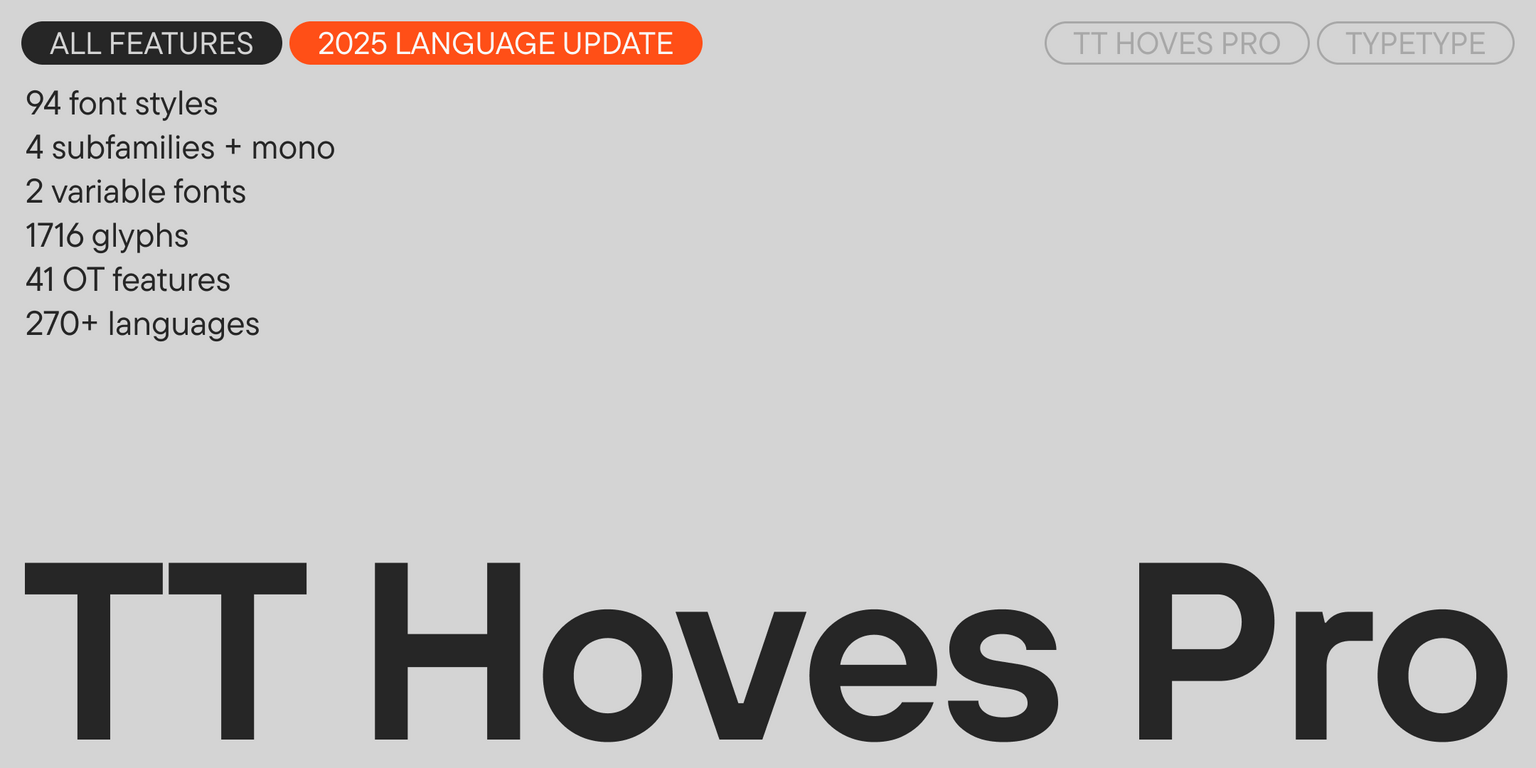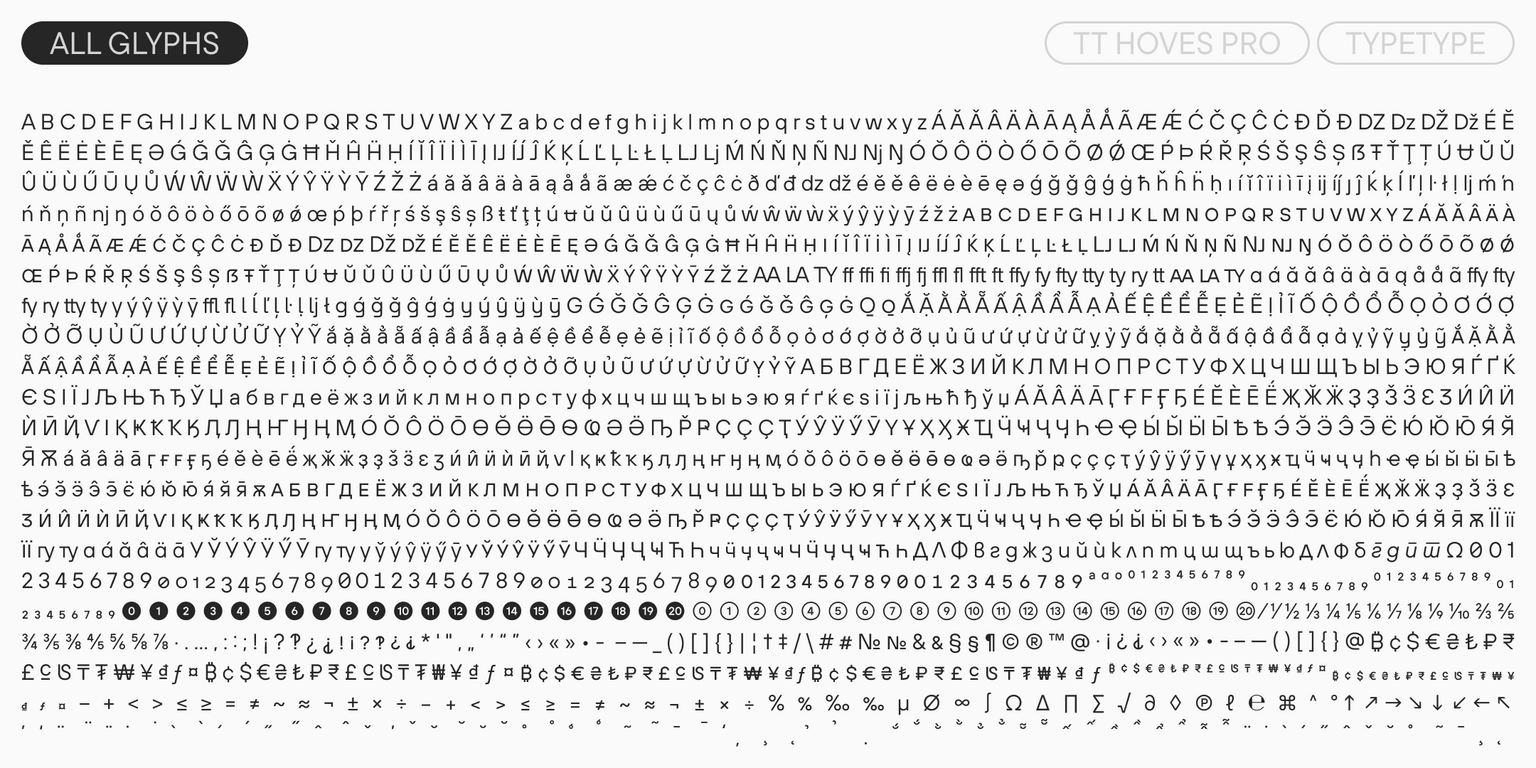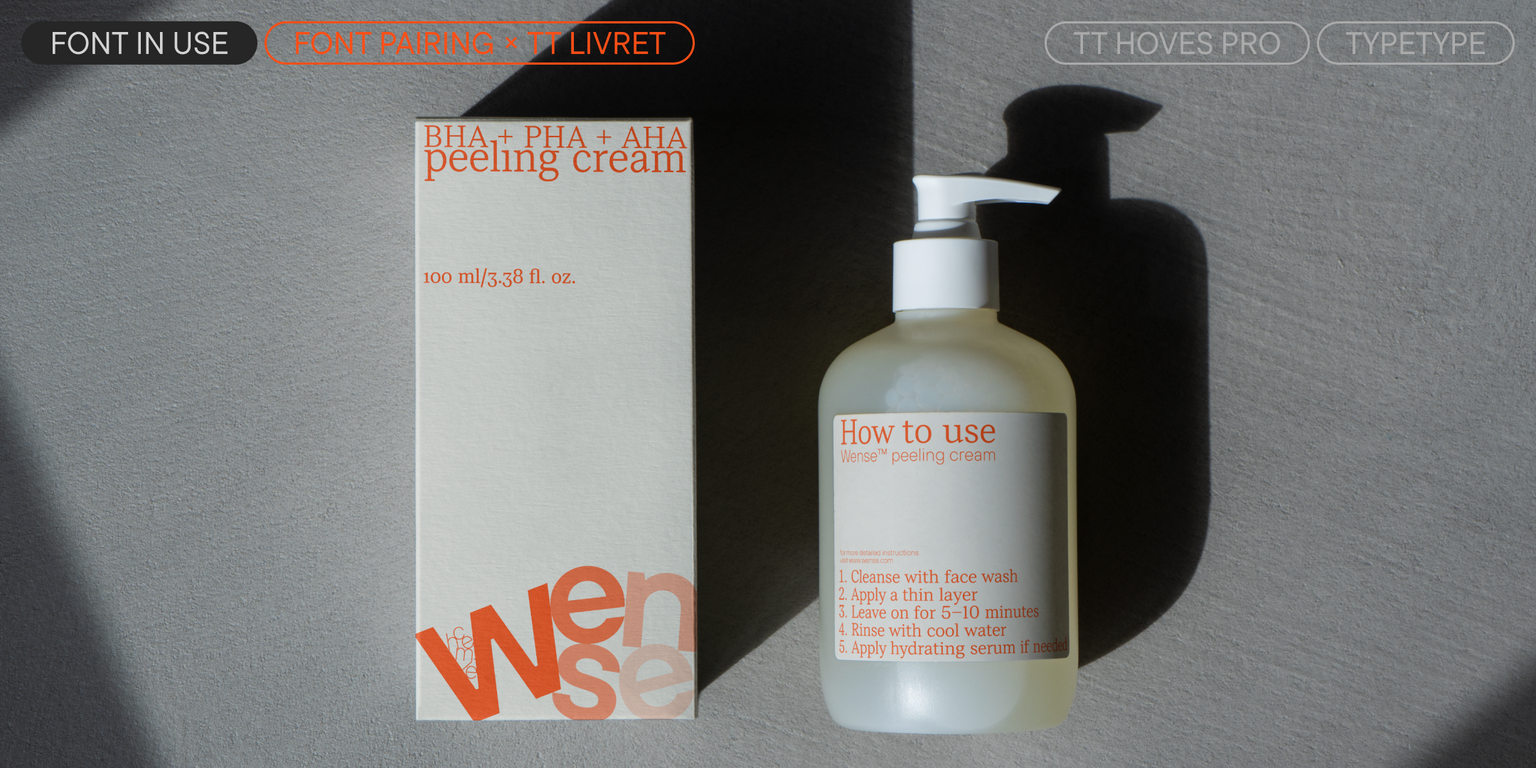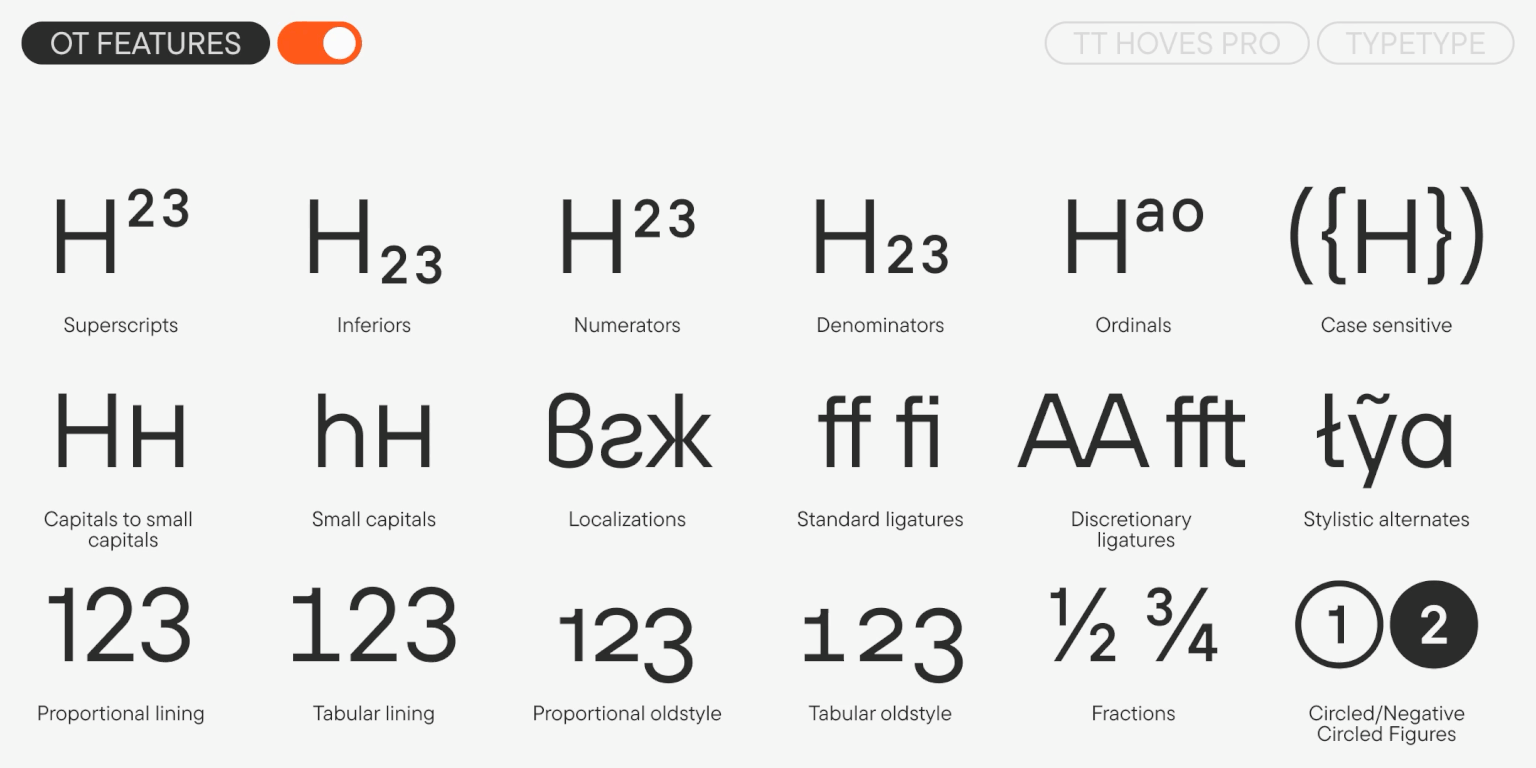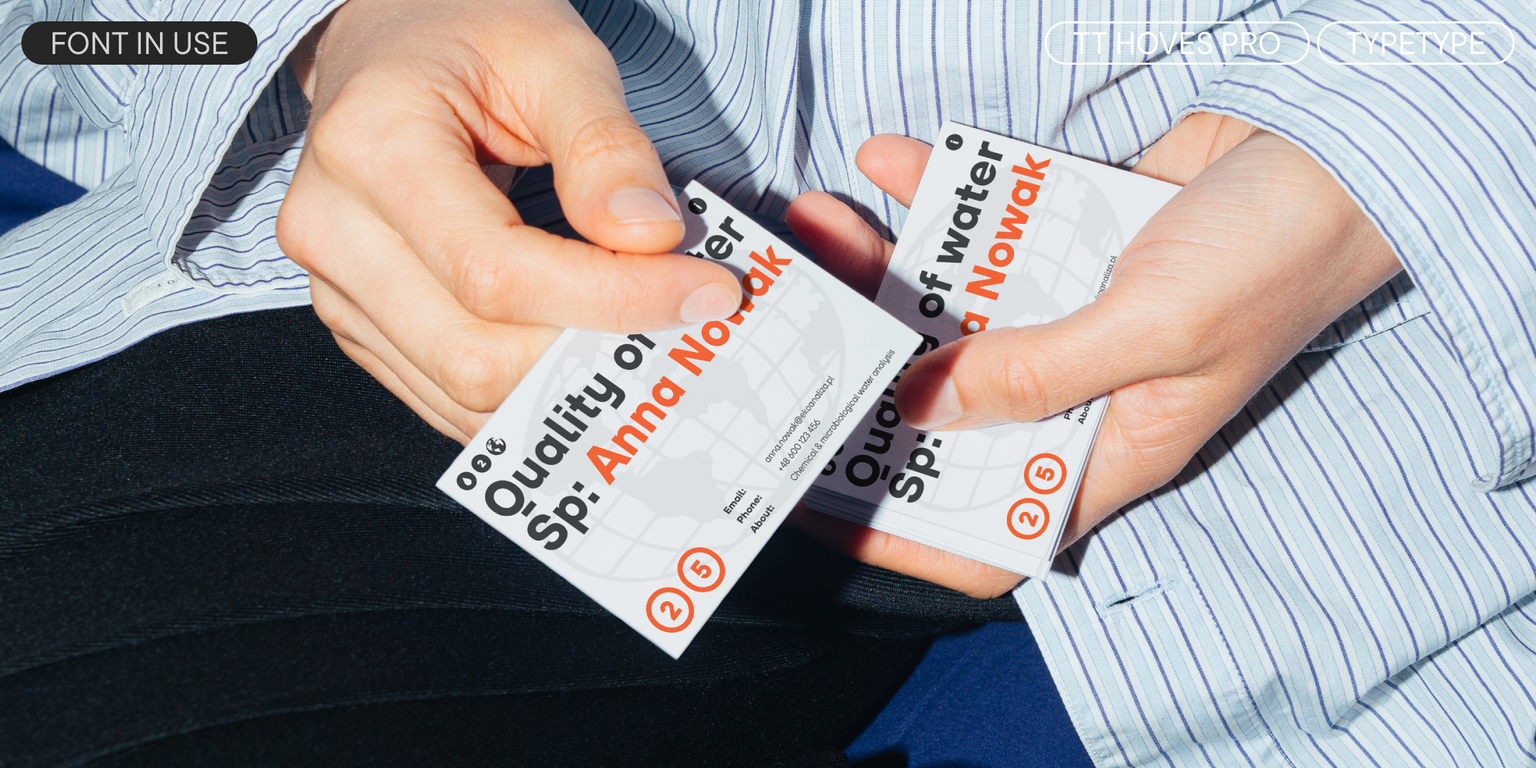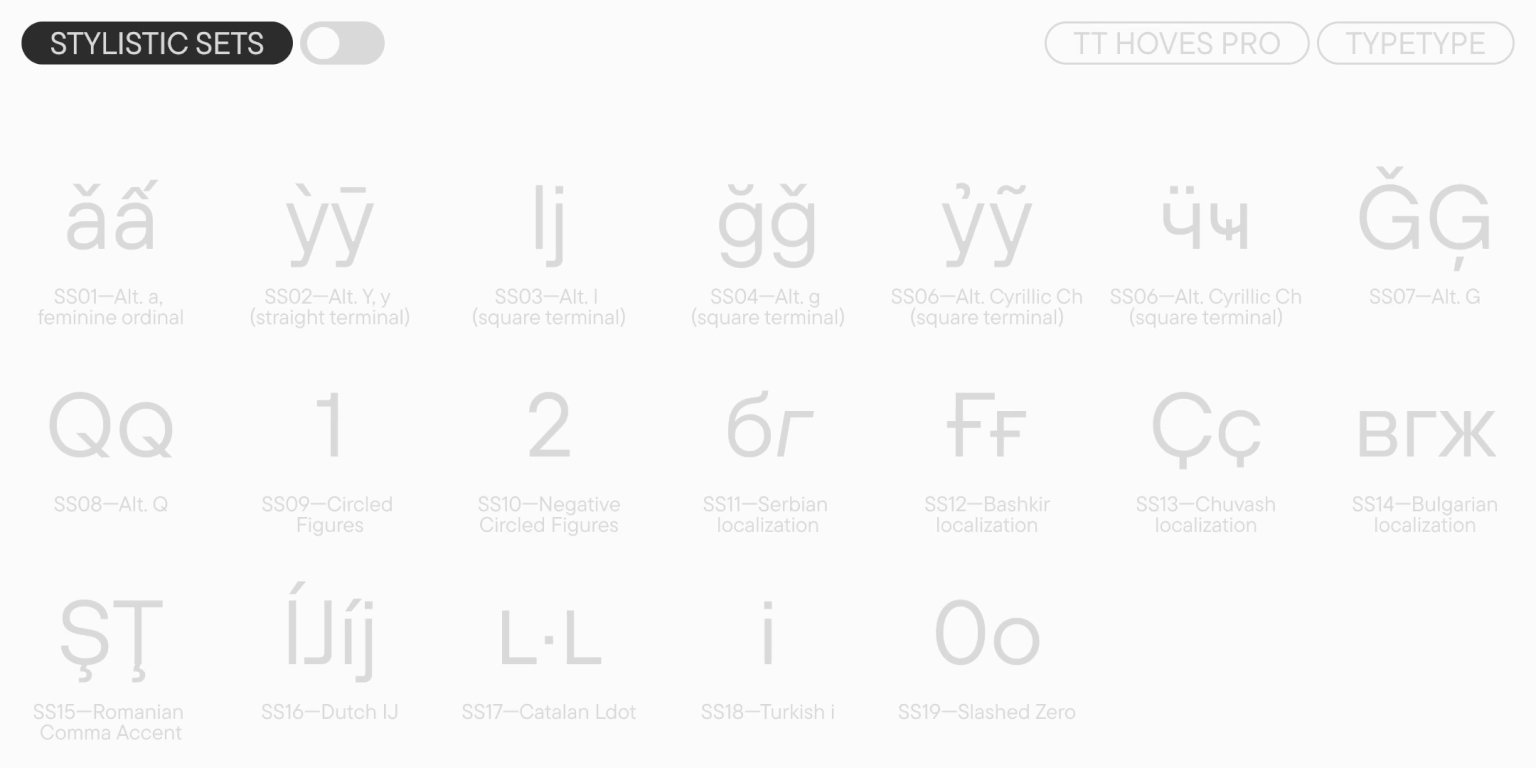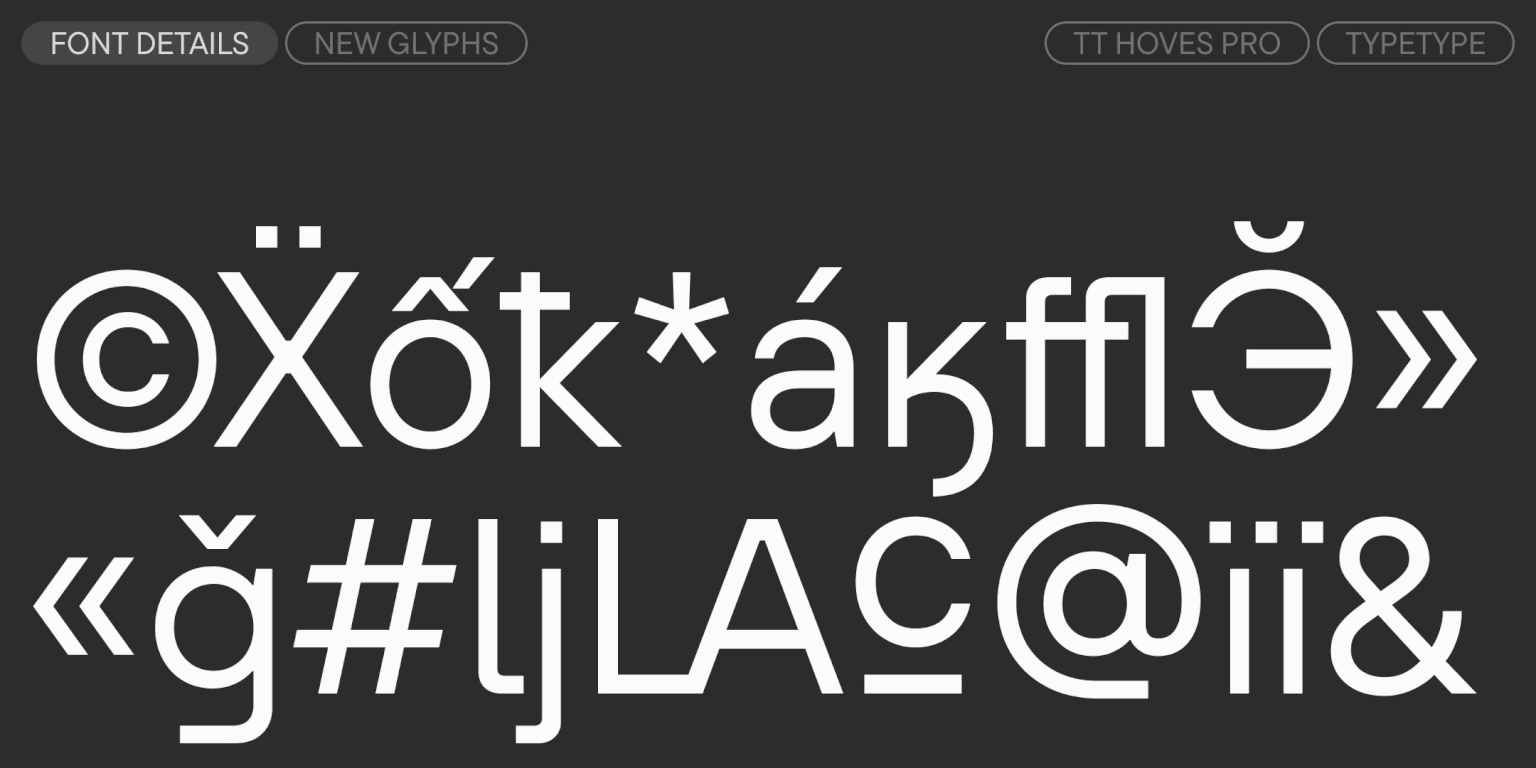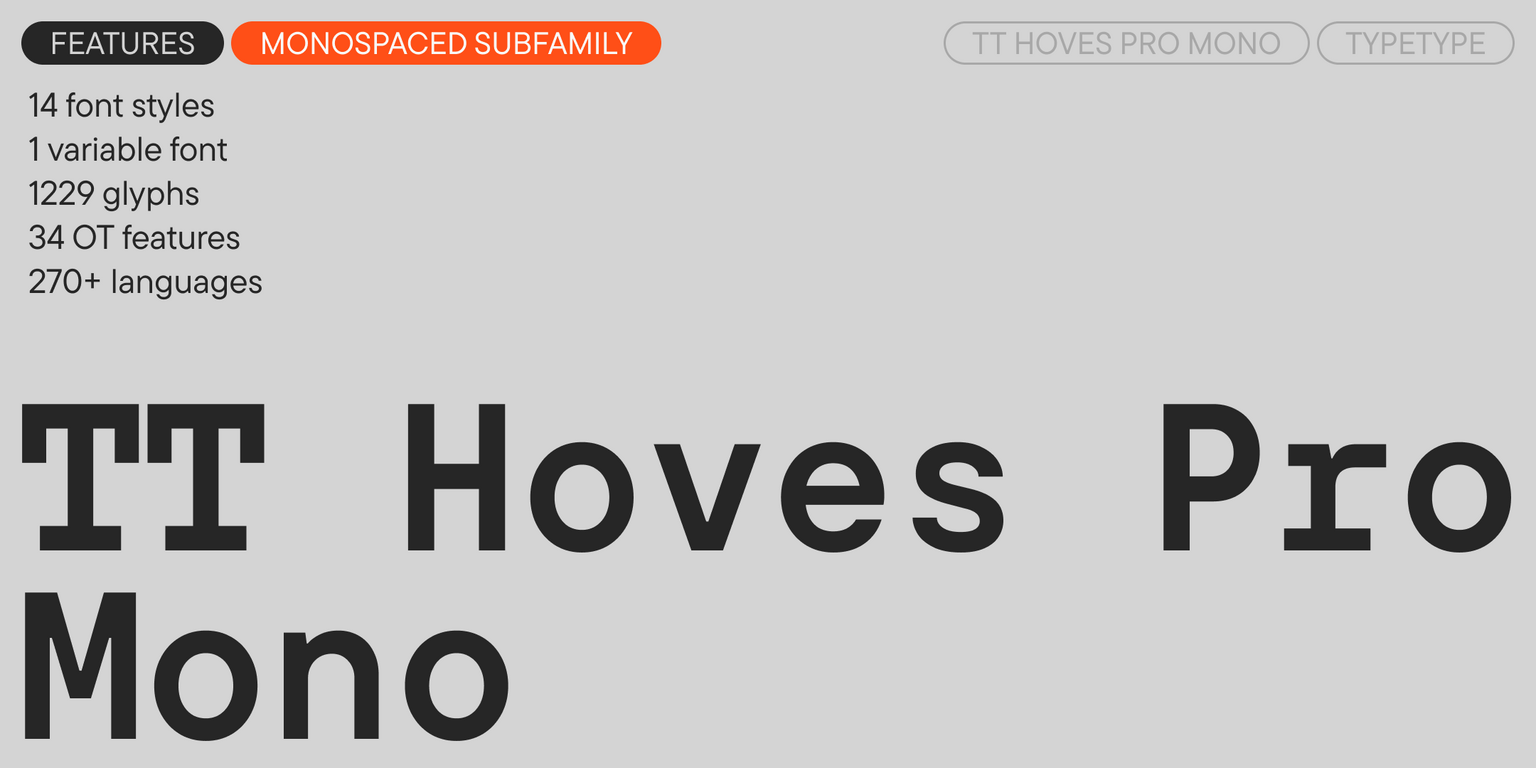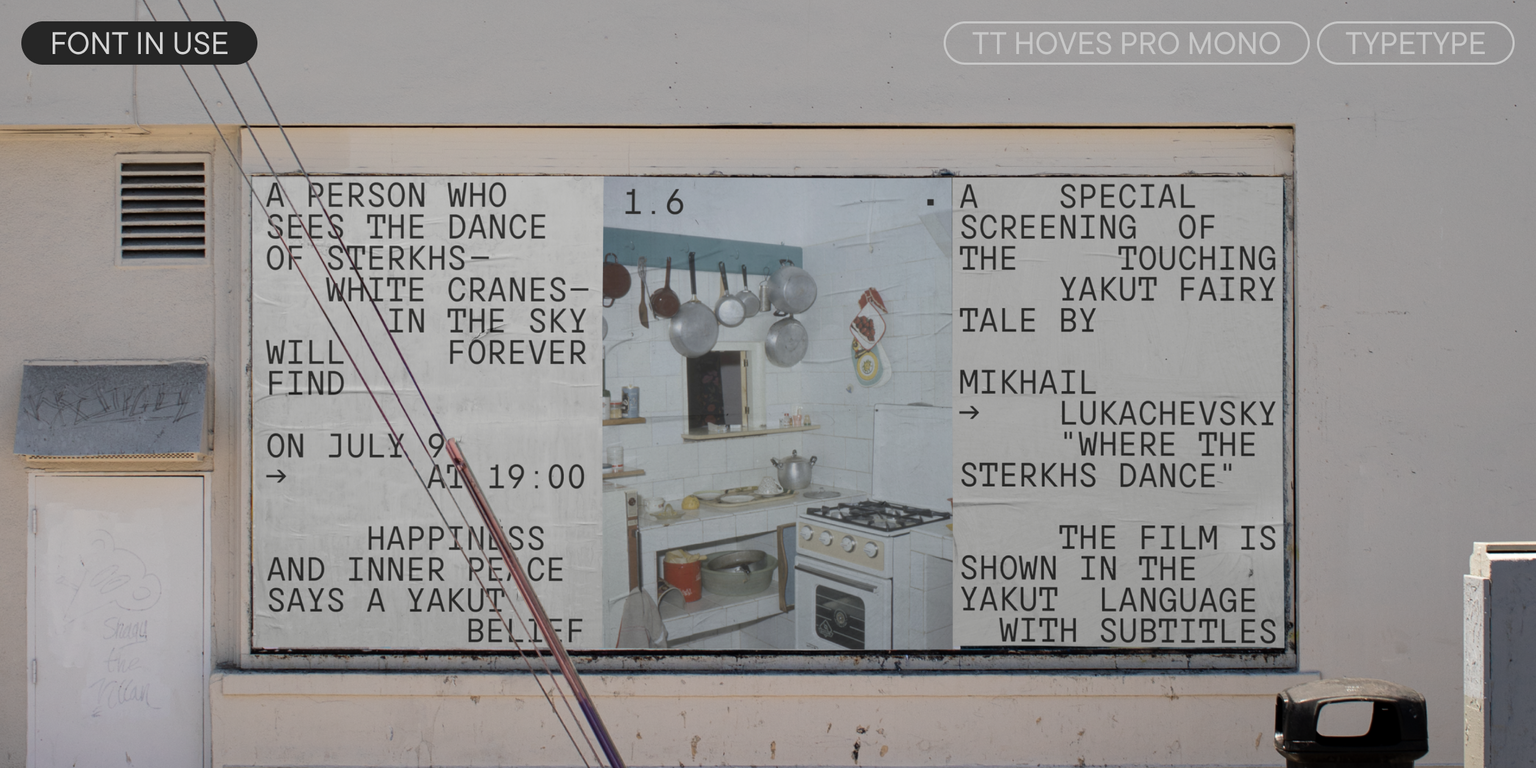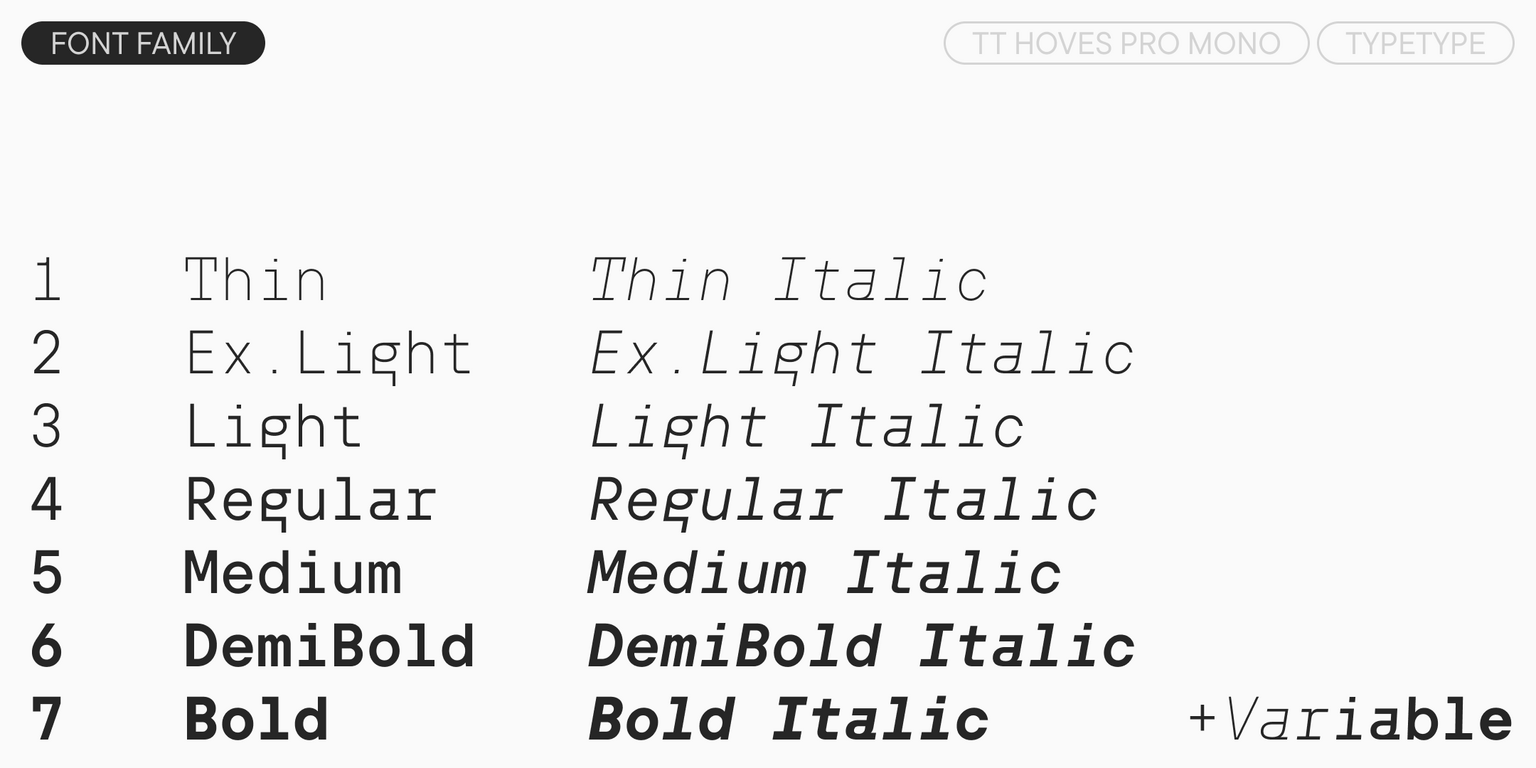
TT Hoves Pro
TT Hoves Pro — ТТ Ховс Про
Произносится «ТТ Ховс Про». «Hoves» — производное слово от horizontal (с английского «горизонтальный») и vertical (с английского «вертикальный»). «Pro» произносится как «про», и является разговорным сокращением слова «профессиональный». Буквы «TT» являются аббревиатурой названия компании.
TT Hoves Pro — скандинавский гротеск с нейтральным, но в то же время узнаваемым характером. Это удобный и функциональный, при этом стильный и эстетичный шрифт для различных задач.